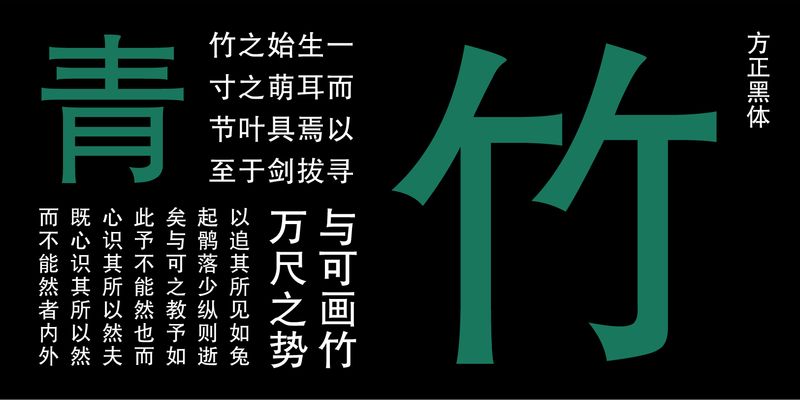
Fāng Zhèng Hēi Tǐ의 디자인은 목판 인쇄 시대의 굵은 글씨체 필사본에서 유래했습니다. Fāng Zhèng Hēi Tǐ는 나팔 모양 같은 전통적인 터미널 디테일을 가지고 있으며 내리 누르는 획, 던지는 획, 인용 부호의 획 두께가 크게 다릅니다. 글꼴의 ZhongGong(카운터와 유사)은 콤팩트합니다. Fāng Zhèng Hēi Tǐ는 중립성과 단순성이 특징입니다. 적당한 두께의 매우 고전적인 텍스트 볼드체이며 매체 용도와 화면 읽기 모두에 적합합니다.